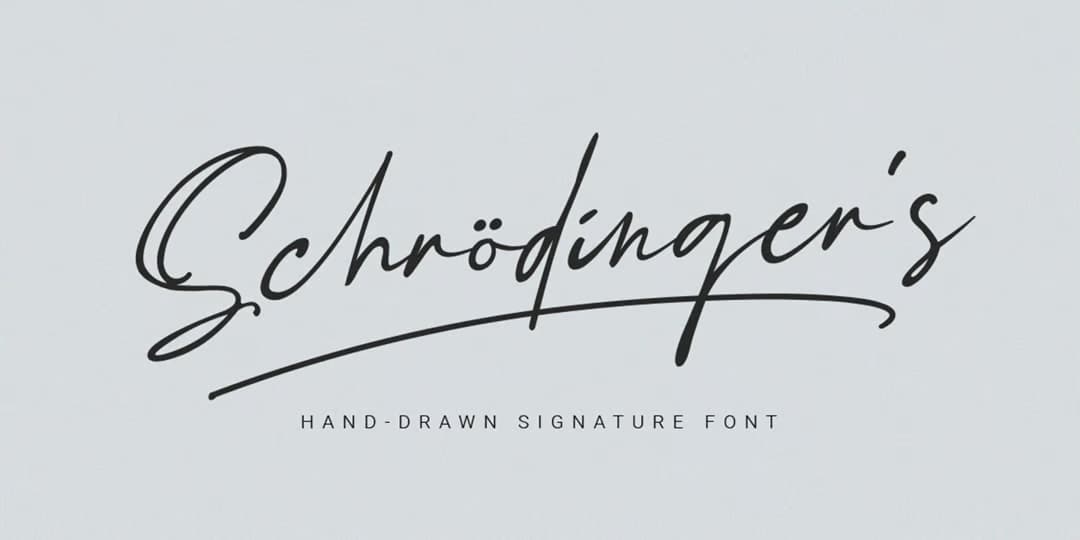
Schrödinger’s Signature
本日は「シュレーディンガーの猫」でお馴染み(馴染んでるか?)、ノーベル賞受賞物理学者エルヴィン・シュレーディンガー Erwin Rudolf Josef Alexander Schrödinger の誕生日(1887)なのでこちら。カジュアルなシグネチャースクリプト。「シュレーディンガー」の名を冠してはいるが、当人とは無関係な模様(笑)。「パイロットのハイテックC(HI-TEC-C)というボールペンで書いた」と作者は述べている。大文字のストロークの一部が二重になっているのが特徴。大文字にオルタネートはないが小文字には160種ほどのかなり多くのリガチャーがあって、文字組のバリエーションが楽しめるようになっている。あと変わってるのがハート型のスワッシュが10種ほどある。何に使うのかは不明。1ウェイト。